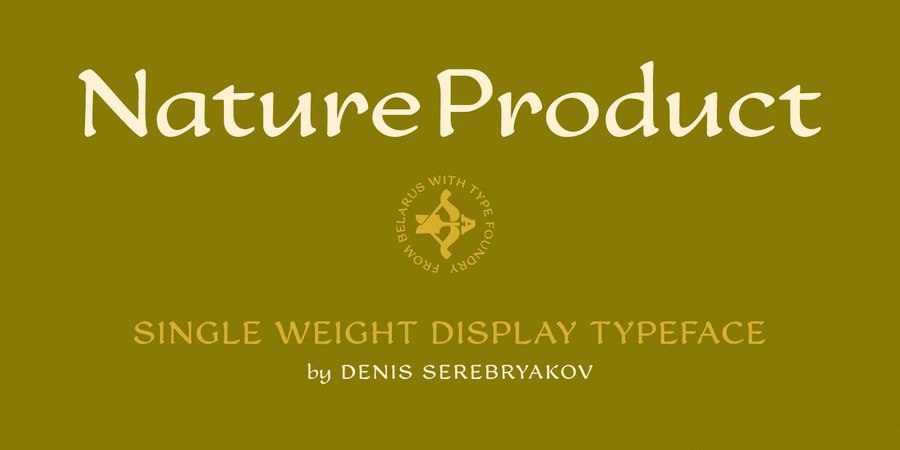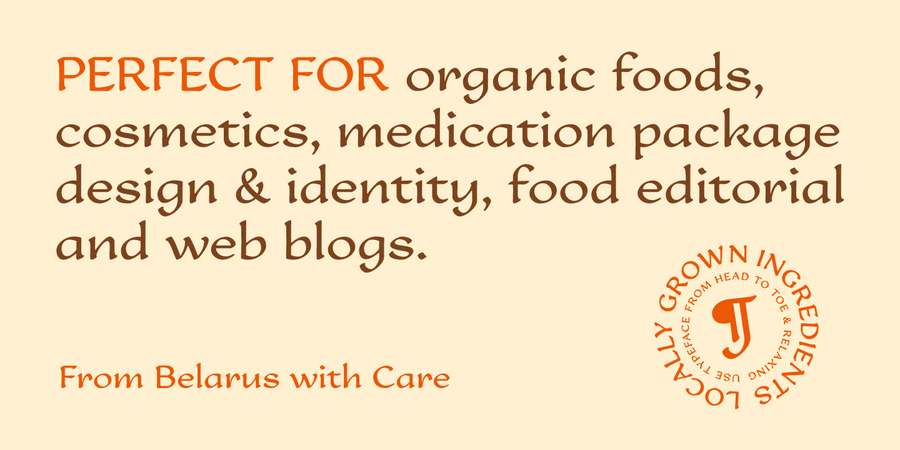
Nature Product (1 шрифт)
Nature Product – це акцидентний шрифт із ідеологією здорового способу життя та харчування. Акуратний контур на основі каліграфії. Шрифт ідеально підходить для використання у дизайні упаковки екологічно чистої їжі, косметики, ліків, а також в айдентиці, друкованих виданнях та відеоблогах. Насолоджуйтеся! Шрифт розробив Денис Серебряков у 2016 році.
Асоціації з сімейством шрифтів Nature ProductОсобистість і характер гарнітури:
приємний, затишний, комфортний, доброзичливий, добрий, ввічливий, спокійний, традиційний, культурний, інтелігентний, освічений, акуратний, оптимістичний, М'який, неквапливий, соковитий, домашній, органічний, смачний, свіжий, довірчий, природний, натуральний, мирний, зручний, архаїчний, древній, племінний, красивий, казковий, старовинний, історичний, майстерний, художній, благородний, виразний, характерний, прекрасний, музичний, творчий, симпатичний, фантастичний, класичний, гуманітарний, динамічний, гармонійний, здоровий, щедрий, добродушний, артізанальний, крафтовий, літній, лісовий, грунтовий
ресторан, вино, їжа, закуска, сік, виставка, здоров'я, природа, вода, кава, смузі, дім, міфологія, скульптура, фентезі, тату, татуювання, квіти, прикраса, казка, музей, мистецтво, музика, Чарівна казка, дієта, кафе, косметика, одяг, краса, живопис, АСМР, література, культура, крамниця, екологія, літо, обід, море, відпочинок, туризм, сувенір, пейзаж, акварель, велнес Гарнітура має ознаки стилів: